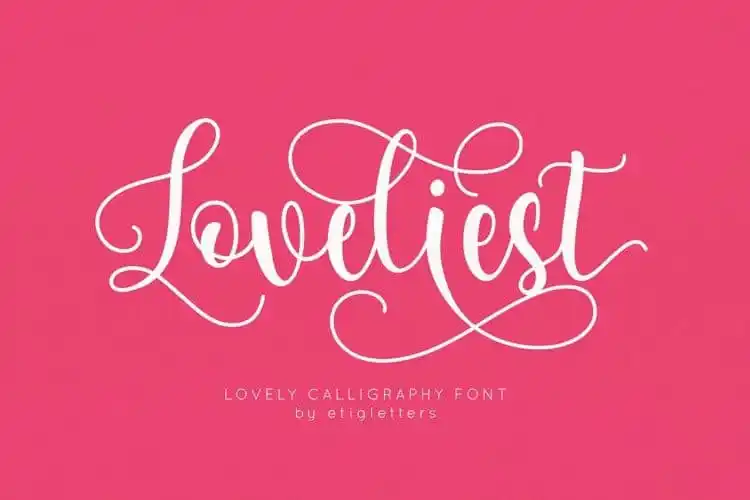
Loveliest Calligraphy Font – Download Grátis
Loveliest Calligraphy Font é uma elegante escolha para projetistas buscando adicionar um toque de sofisticação a suas criações. Seja você criando materiais de bordado, organizando casamentos, desenvolvendo marcas corporativos ou qualquer outro tipo de projeto, esta fonte proporciona resultados perfeitos e impressionantes. Ideal tanto para designers iniciantes quanto profissionais experientes, Loveliest Calligraphy é versátil o suficiente para atender a uma variedade ampla de necessidades de design. Seja um enredo sofisticado que você deseje criar para seus materiais de bordado, ou um convite de casamento perfeito com o toque personalizado e cuidadosamente pensado que você deseja incluir, Loveliest Calligraphy pode atender a todos esses requisitos. Além disso, ela também se adapta bem ao seu trabalho em marcas corporativas, tornando-a uma fonte indispensável para designers buscando um olhar elegante no seu trabalho. Não importa o tipo de projeto que você está executando, Loveliest Calligraphy estará sempre pronta para oferecer resultados impecáveis. Isso a torna não apenas uma excelente opção para designers iniciantes, mas também para aqueles que procuram adicionar um toque especial e único aos seus projetos.